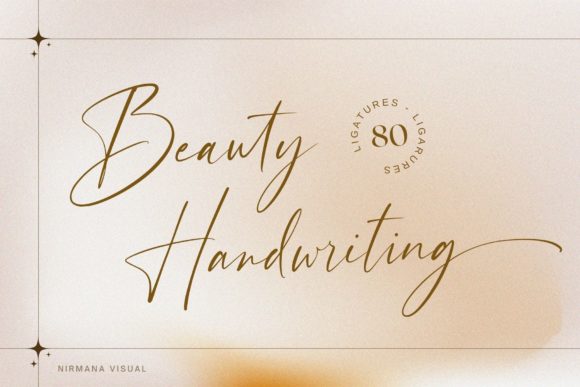
Beauty Handwriting
قد يكون العثور على عناصر التصميم المناسبة أمرًا صعبًا، ولكن Beauty Handwriting يقدم مجموعة استثنائية ترتقي بعملك على الفور.
سواء كنت تقوم بإنشاء منتجات الطباعة عند الطلب أو دعوات الزفاف أو رسومات وسائل التواصل الاجتماعي، فإن Beauty Handwriting هو الخيار المثالي.